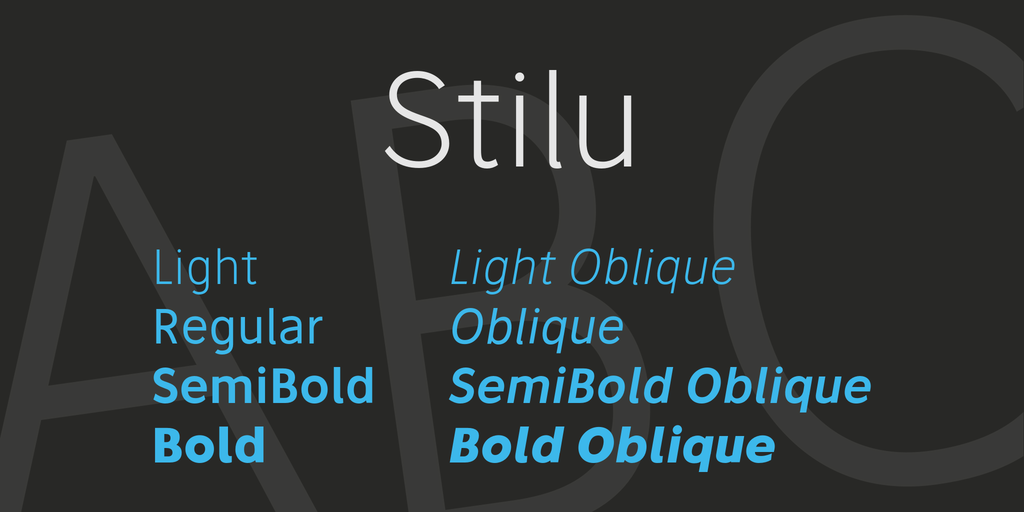
Stilu Font Family
A Stilu Font Family é uma família de tipografia sans-serif que traz quatro pesos diferentes para sua coleção: Luminoso, Regular, SemiBold e Negrito. Esta paleta de cores também inclui suas versões obliques, criando um conjunto bem diversificado e funcional. Os designers da Stilu tiveram cuidado em incorporar detalhes únicos na fonte, como as ligaduras (ligações entre letras), o uso das figuras capital pequena para garantir estética legível em textos menores, a opção de usar as figuras capítulos antigas e modernas. Esses recursos são essenciais para aqueles que buscam uma fonte elegante e versátil, adequada para diversos usos, desde o design editorial até a criação de logotipos. A Stilu é uma excelente escolha para quem busca tanto harmonia quanto força no seu trabalho visual.